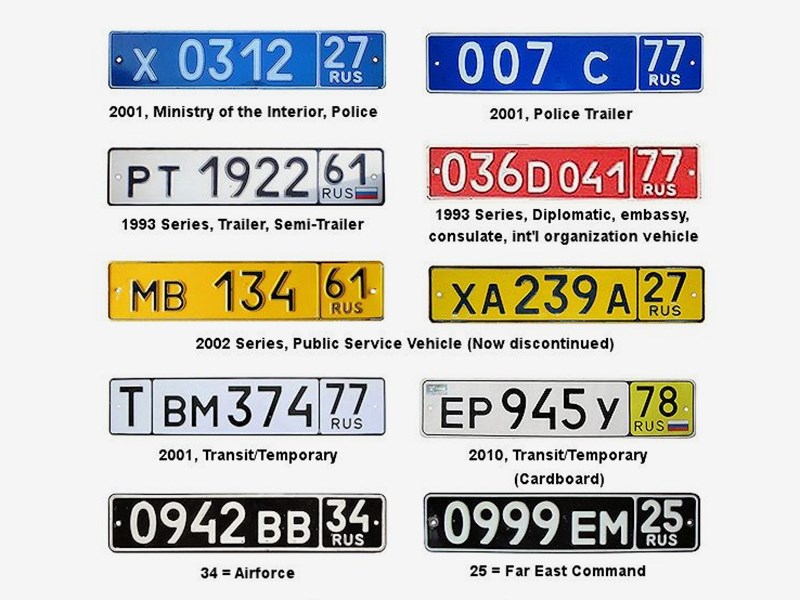
Шрифт для регистрационных номерных знаков (автомобильных номеров) / Хабр
Разработка комплексной автоматизированной системы, целью которой является автоматизация механизма контроля доступа на основании системы распознавания номерных знаков, сложная и, несомненно, комплексная задача.
Для ее решения, в рамках квалификационной работы на степень бакалавра, мне потребовался не один месяц, и не одна сотня чашек чая.
Сегодня посмотрим на алгоритм и результаты решения локальной задачи по созданию шрифта в векторном формате согласно нормативной документации для отображения эталонов символов при корреляционном распознавании. На первом этапе углубимся в суть решаемой задачи.
1 «Матчасть»: Регистрационный номерной знак Российской Федерации
Согласно ГОСТ Р 50577-93 «Знаки государственные регистрационные транспортных средств. Типы и основные размеры. Технические требования» большинство регистрационных знаков имеют вид, указанный на рисунке ниже.
Рис. 1.
Стандартные размеры регистрационного знака, которые составляют 520×112 мм. Символьные комбинации на стандартных номерных знаках определяются тремя буквами и тремя цифрами. Вышеприведенный ГОСТ Р 50577-93 ссылается на использование 12 букв кириллицы, которые имеют графические аналоги в латинском алфавите: А, В, Е, К, М, Н, О, Р, С, Т, У и Х.
Надо заметить, что буквы по размеру шрифта меньше, чем цифры.
Начертание символов определяется шрифтом ЖР5 по ГОСТ 3489.2-71 «Шрифты типографские. Гарнитура Журнальная рубленая». На рисунке ниже приведена область из ГОСТа начертания шрифта для кеглей от 12 и выше.
Рис. 2.
Перед решением задачи, всегда необходимо провести исследование и определить «Решили ли уже эту задачу до меня?» и «Каким образом, ее решили?». Следовательно, перейдем к следующему этапу, а именно поиску.
2 «Поиск»: Шрифт для автомобильных номеровПоиск в интернете был недолгим, по правильному запросу «шрифт автомобильный номер», корпорация добра с радостью сообщила, что шрифт в векторе доступен для бесплатной скачки.